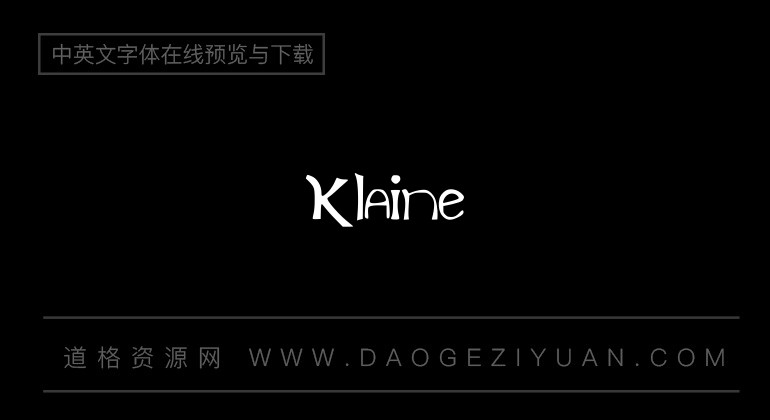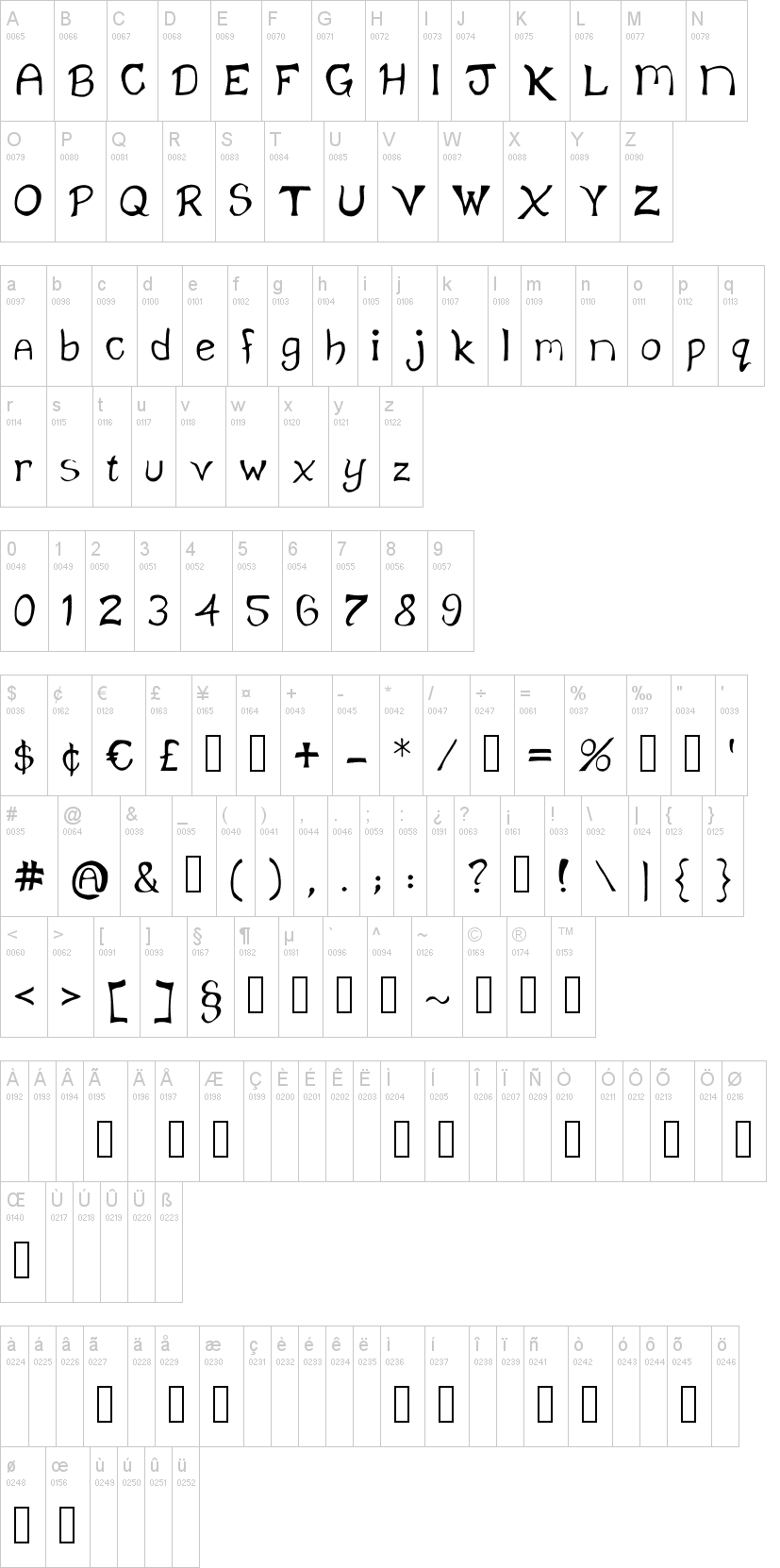
Klaine
Klaine 是一款由荷兰设计师 Klaas de Vries 创作的字体。Klaine 是一款混合字体,它结合了英文和拉丁字母的特点,使字体看起来更加清晰、简洁、美观。Klaine 字体的字体设计更加细腻,字体的线条更加顺滑,能够更好地表达文字的细节。Klaine 字体采用了许多技术,使其具有良好的可读性,能够更好地展示文字的细节,让文字更加易读。
Klaine是一款非常不错的手写艺术字体,具有很好的视觉感,适合于文化类的宣传设计、商业类品牌的广告和产品包装设计以及个性化文字排版等较多场景。